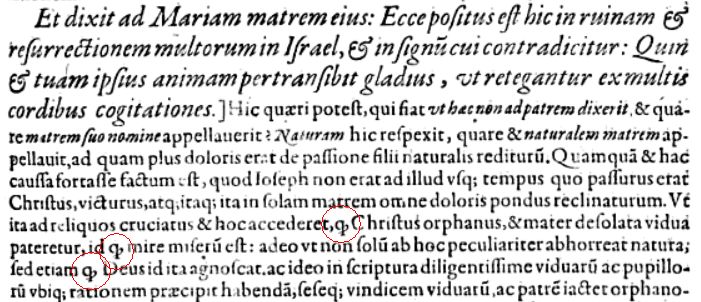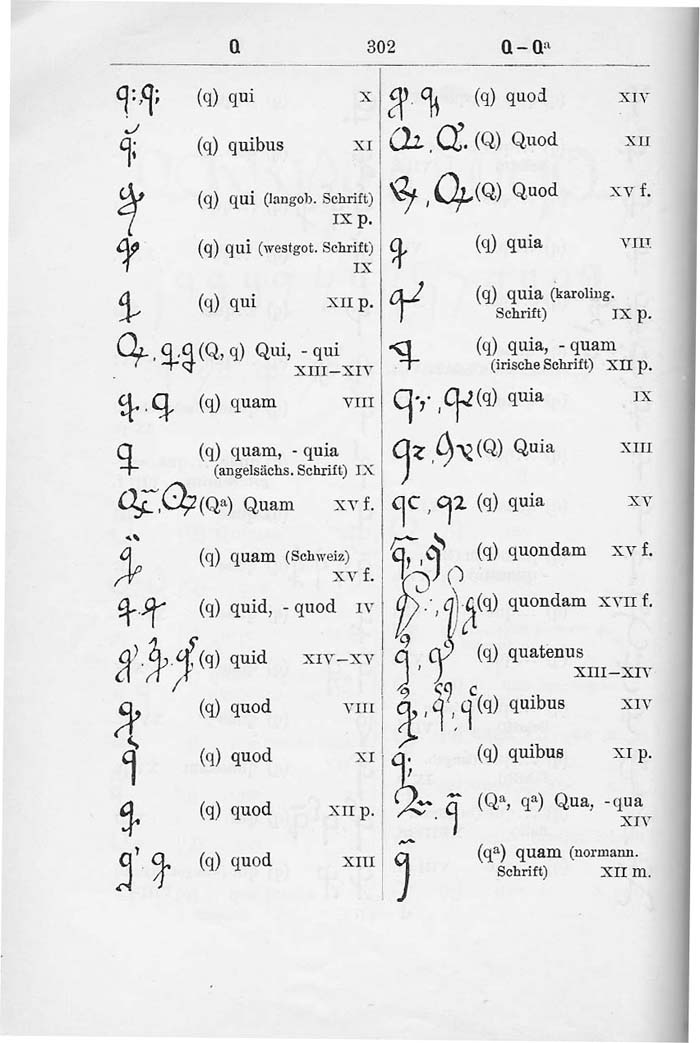
Ligatur zu identifizieren.
Hallo Freunde, kann jemand die unterste Ligatur identifizieren? Und zwar müßte ich zum einen wissen, wie die Ligatur ausgeschrieben wird (quia? quod? quare?), zum anderen welches Unicode-Zeichen dem entspricht (LATIN SMALL LETTER Q WITH DIAGONAL STROKE? LATIN SMALL LETTER Q LIGATED WITH R ROTUNDA?).
Und da es bei diesen historischen Abbreviaturen einfach zu viele gibt, gibt es dafür, genau wie für die ja weit wenigeren Fraktur-Ligaturen keine Unicodes, und möchte man die im Font anbieten, wie es beispielsweise Alter Litera mit seiner kompletten Gutenberg-Schrift macht, sind diese nur über OpenType-FDunktionen azfrufbar. Ich würde dies dann z.B. über die Ligatur-Funktion machen, indem dann das abgekürzte Wort dann zusammen mit einem Steuerzeichen, beispielsweise * oder # komplett geschrieben wird, und dadurch dann in die Abbreviatur gewandelt wird. So ähnlivhj, wie ich dies für meine Bienchen SAS für die 1. Klasse "Zensur"-Stempel gemacht habe.
Stimmt, es ist keine Ligatur, sondern eine Abbreviatur. Sehe gerade, daß diese Abbreviatur wohl für “quod” steht. Zumindest gibt es in diesem Dokument hier drei Scan-Aussschnitte mit dem Hinweis auf “quod”: http://www.textcreationpartnership.org/docs/dox/latabbrs.html
Das Problem mit Cappellis Werk ist, daß er wild alles durcheinanderwirft: verschiedene Zeiten, Buchdruck und Handschrift, verschiedene Länder und Regionen, verschiedene Sprachen. Das ist einfach zu wild. Man muß die Zeit eingrenzen und am besten ein Verlagshaus betrachten, dann bekommt man schon eine geordnetere und überschaubarere Übersicht über den gängigen Vorrat an Abbreviaturen.
Es gibt zwar unheimlich viele Abbreviaturen, aber die, die es bis in den Buchdruck geschafft haben, kann man fast an zwei Händen abzählen! Das sind nur ganz wenige! Da wäre ein Unicodezeichen ziemlich angebracht. “P” mit Schweif gibt es ja auch im Unicode, um nur ein Beispiel zu nennen. Außerdem wäre da noch die Frage, was das für ein Ärmchen da an dem “q” ist, welche Entstehungsgeschichte es hat. Und wie ich es nun möglichst originaltreu abbilden (transkribieren) kann.
Also nochmal ausführlich. Es erscheint in dem Druck “Enarrationes, sive postillae majores, in lectiones …” von Martin Luther, gedruckt 1617 in Frankfurt.
Also mein hauseigener Latinistik-Promovent sagt die Abbreviatur stehe für quod und beschwert sich über Luthers schlechtes Latein ;-) allerdings seien die Abbreviaturen immer nur im Kontext des ganzen Druckes zu sehen, um sagen zu können, was sie bedeuten. Hier noch mal die Seite aus dem Cappelli (Buchstabe Q, Seite 3):
Allerdings ist der Cappelli für Handschriften und nicht für Drucke, kann hier aber trotzdem benutzt werden, weil die Drucker die Handschrift natürlich aufgreifen.
TobiW, bedanke mich für deine Hilfestellung! Ich denke auch, quod ist richtig, obwohl diese Seite hier “quia” behauptet: http://www.webalice.it/claudiusdubitatius/Trivium/Folia/Ilias_1.htm Das ist wenn nicht grob falsch, so doch zumindest in 90% der Fälle falsch :-), nach den Fällen zu urteilen, die ich mittlerweile gesichtet habe.
Und Luthers Latein … naja, ich würde sagen: der darf das! Schließlich hat er auch einige neue dt. Wörter geprägt, er hatte einfach einen anderen, ungezwungeneren Umgang mit Sprache als Goethe oder Cicero.
Die Frage ist auch, im Vergleich wozu sein Latein “schlecht” ist. Immerhin hatte die Sprache einiges auf dem Buckel. Goethe würde sich sicher auch über unser Deutsch beschweren.
Die konjugierte/deklinierte Form ergibt sich aus dem Kontext. Die Abbreviatur gibt bisweilen nur die Form an, unter der man das Wort, sofern man weiß, was es bedeuten soll, im Lexikon finden kann.
Latinisten sortieren ihre Sprachperioden in eine goldene, silberne, ... Latinität ein. Alles, was nicht Caesar oder Cicero ist, ist minderwertigeres Latein :( Hierzu könnte man jetzt eine treffliche Diskussion führen, die der ähnelt, welche Orthographie denn nun die richtige sei.
Och, ich wäre mir da nicht so sicher. Goethe war ein an allem interessierter Forscher. Außerdem schuf er Sprache und konsumierte sie nicht nur in Texten. Den Sprachwandel der letzten 200 Jahre könnte er faszinierend und inspirierend finden. In die dumpfe Früher-war-alles-besser-Denke der heutigen Sprachpfleger würde er wohl nicht einstimmen.
Solche Vergleiche »damals Hochkultur, weil Goethe—heute Verfall, weil Einzelbeispiel mit Rechtschreib-/Ausdrucksschwächen« taugen doch gar nichts. Das sind die berühmten Äpfel-und-Birnen-Vergleiche.